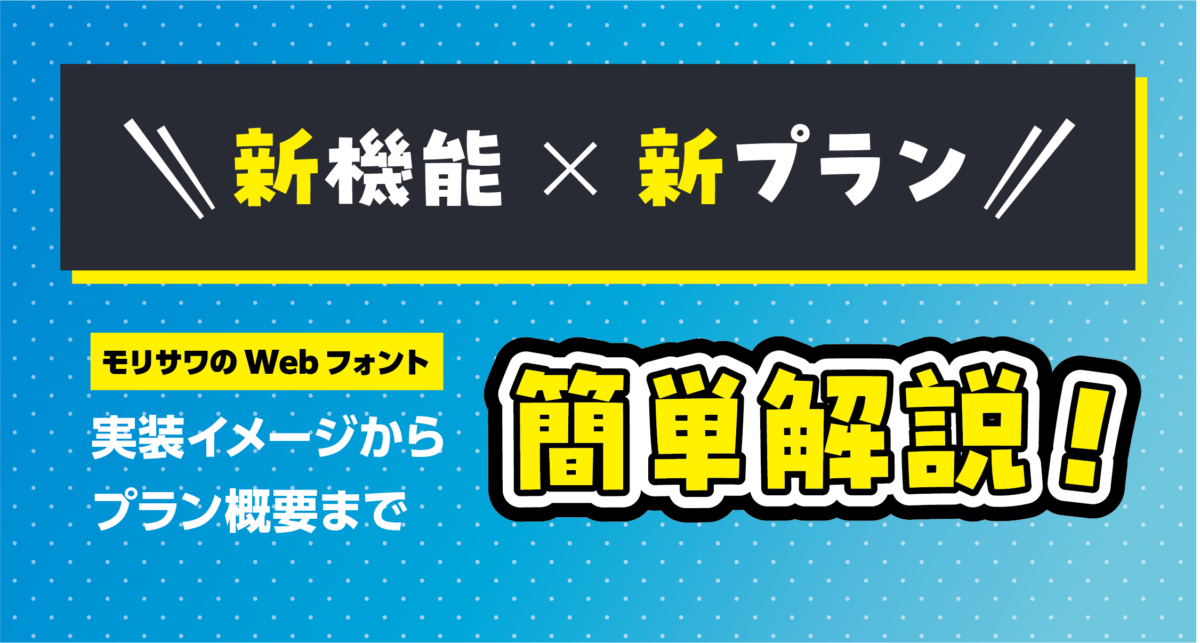
企業サイトやブランドページにおけるデザイン強化・ユーザー体験の向上などを目的に、Webフォントの導入を検討する企業が増えています。
一方で、いざサービスを選ぼうとすると、こんな課題に直面することも多いのではないでしょうか?
- Webフォントとして利用できる書体バリエーションを確認したいなど……
そこで今回は、モリサワがご提供しているWebフォントサービスのプラン拡充および機能アップデートが2025年5月に行われましたので、改めてプラン概要やWebフォント実装時のイメージをご紹介します。
1. はじめに:モリサワのWebフォントサービス
モリサワのフォントサブスクリプションサービス「Morisawa Fonts」では、印刷文化を支えてきた高品質なフォントをWebサイトにもご利用いただけるようWebフォント用のプランもご用意しております。
2025年5月に行われたMorisawa FontsのWebフォントプランに関するアップデート内容は以下の通りです。
- 手軽にWebフォントを導入できる新プラン「Webフォント Lite」を提供開始
- 従来プラン「Webフォント」にて円滑なプロジェクト運用をサポートする機能をアップデート
- 利用可能な書体ラインナップの拡充
2. 実装イメージのご紹介
今回のアップデートにより、人気の「ヒラギノフォント」「写研フォント」「秀英体ファミリー」も新たにWebフォントとしてご利用いただけます。
「みちくさ」「澄月」といったフォントにおいては、文脈を考慮した連綿体(平安時代の書物を起源とした続け字)の設定が可能になりました。日本の伝統美をWeb上でも活かすことができるようになり、デザインの幅が広がります。
【連綿体サンプル】
ありがとう
みちくさ(連綿体あり)
ありがとう
みちくさ(連綿体なし)
ありがとう
澄月(連綿体あり)
ありがとう
澄月(連綿体なし)
また、text-spacing-trimプロパティを使うことで、約物のアキを適切に設定することができるようになりました。
句読点や括弧などの約物(記号類)には前や後ろにアキ(スペース)があることが多いですが、約物が連続したり、行頭・行末に置かれたりする際のアキを制御できるようになり、より自由なWeb組版を実現します。
【文字詰めサンプル】
「フォーマルなツデイと広告ディスプレイ志向のアローG シリーズの中間に位置づけしたモダンサンセリフ」。1986年、「新ゴ」の開発をスタートする際、モリサワの社内文書に記された文である。まず目にとまるのは、「モダン」という言葉である。モダンの対照となる言葉は「オーソドックス」。伝統的な、保守的な、といった意味だ。
text-spacing-trim:trim-startで組んだ文章
「フォーマルなツデイと広告ディスプレイ志向のアローG シリーズの中間に位置づけしたモダンサンセリフ」。1986年、「新ゴ」の開発をスタートする際、モリサワの社内文書に記された文である。まず目にとまるのは、「モダン」という言葉である。モダンの対照となる言葉は「オーソドックス」。伝統的な、保守的な、といった意味だ。
text-spacing-trim:space-allで組んだ文章